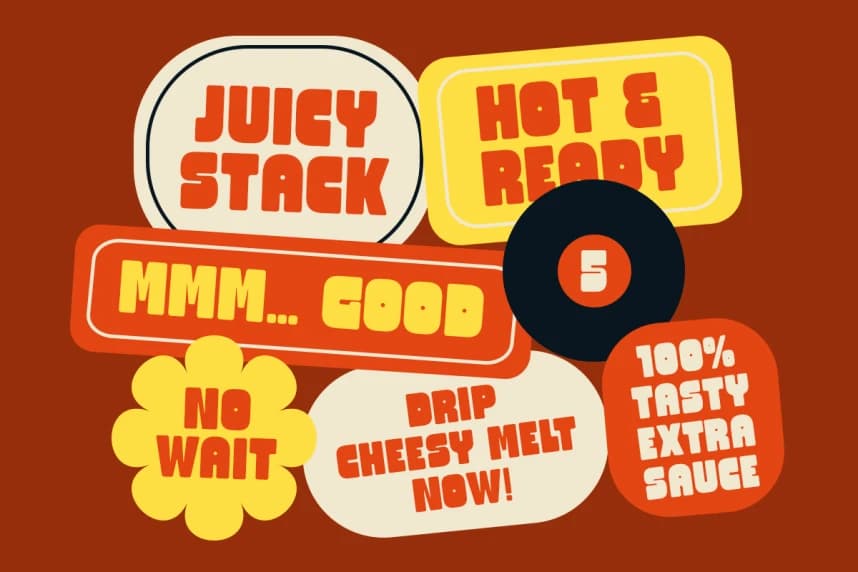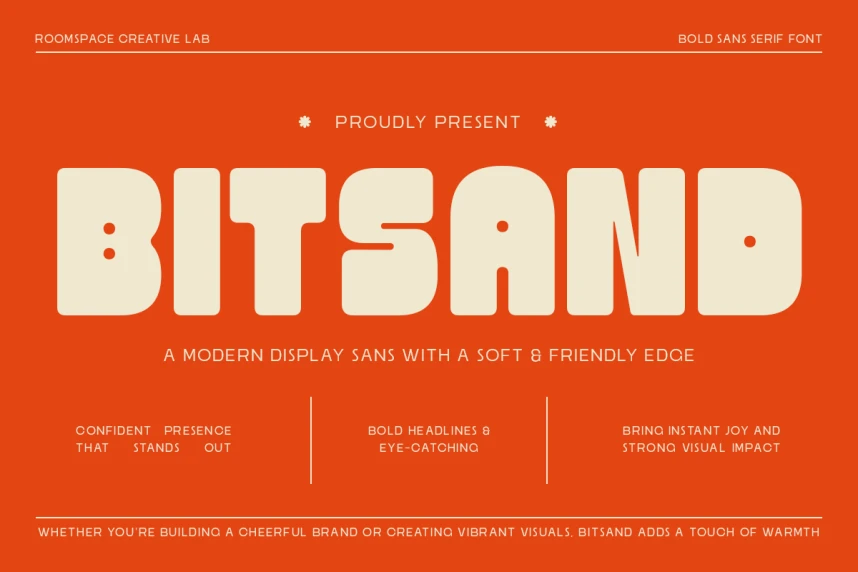
Bitsand Font – Bold Playful Display Font, tasarımlarınıza sıcaklık, enerji ve kişilik katması için tasarlanmış gösterişli bir sans-serif fontudur. Yuvarlak hatları ve yumuşak kenarlarıyla dostça ve yaklaşılabilir bir ton yaratır; aynı zamanda güçlü bir görsel etki de sağlar.
Bitsand Font – Bold Playful Display Font, tasarımlarınıza sıcaklık, enerji ve kişilik katmak için tasarlanmış kalın ve gösterişli sans-serif yazı tipidir. Yuvarlak hatları ve yumuşak kenarlarıyla dostça ve yaklaşılabilir bir ton yaratırken aynı anda güçlü bir görsel etki sağlar.